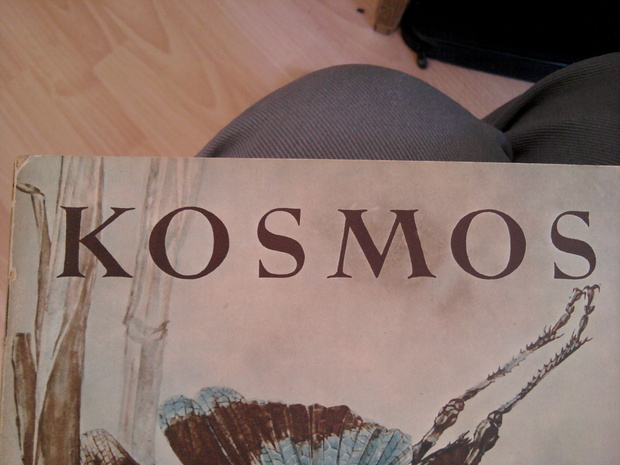
Kosmos Schrift gesucht
ich finde mal wieder nicht raus was für eine Schrift verwendet wurde.
Gefunden habe ich die schöne Antiqua auf dem Cover eines antiquarischen Heftes
ich weiß leider nicht mehr in welchem Verlag das Heft erschien, ich hab es nur fotografiert.
der Font erinnert an diese beiden
Kann es sein, dass der Schriftzug gezeichnet ist? Wenn mich nicht alles täuscht, dann unterscheiden sich die beiden »O« und die beiden »S» deutlich voneinander, was ein starkes Indiz für eine handgezeichnete Schrift ist. Wäre Dir geholfen, wenn wir ähnliche Schriften nennen?
Ich glaube nicht, dass der Schriftzug gezeichnet ist, es scheint nur so, weil ich das Heft perspektivisch verkürzt fotografiert habe. Wahrscheinlich wurde die Schrift einfach nie digitalisiert.
Aber ja es würde mir sehr helfen wenn Ihr ähnliche Schriften nennt
Verlegt wurde das heft von der "Franckh´schen Verlagshandlung Stuttgart"
Hier sind noch andere Hefte der Reihe:
Ähnlich wäre die
Das S und auch das M mit den doppelten Serifen in deiner Vorlage sind aber schon sehr speziell …
Ah, super
das M und das S der Cochin ähneln der gesuchten Schrift wirklich sehr.
Das K ist aber dem der Perpetua ähnlicher